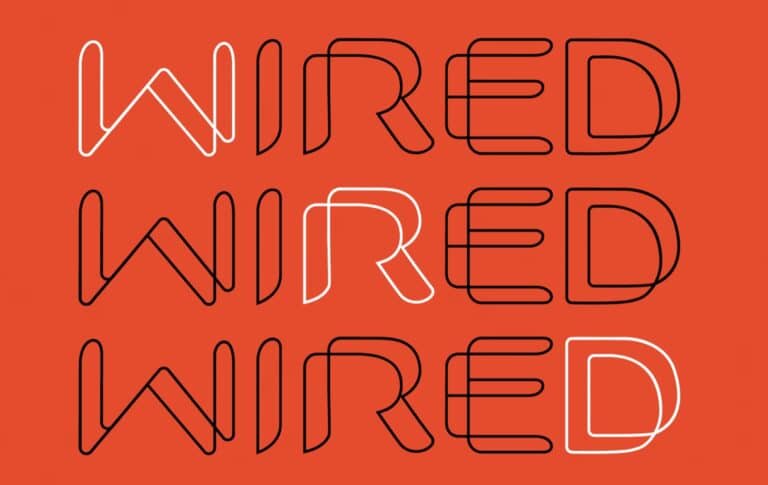
Freefont Wired
Aus nur einem Strich besteht die neue Schrift von Free Goodies for Designers.
Wired eignet sich vor allem für dekorative Gestaltungen in großen Größen. Dann sehen die Buchstaben von Marcelo Reis Melo, einem der Mitglieder der kreativen Gruppe Free Goodies For Designers aus Stockholm richtig gut aus, zumal die Linienführung einen 3D-Effekt simuliert. Der Freefont verfügt über Großbuchstaben, leider fehlen aber Umlaute.